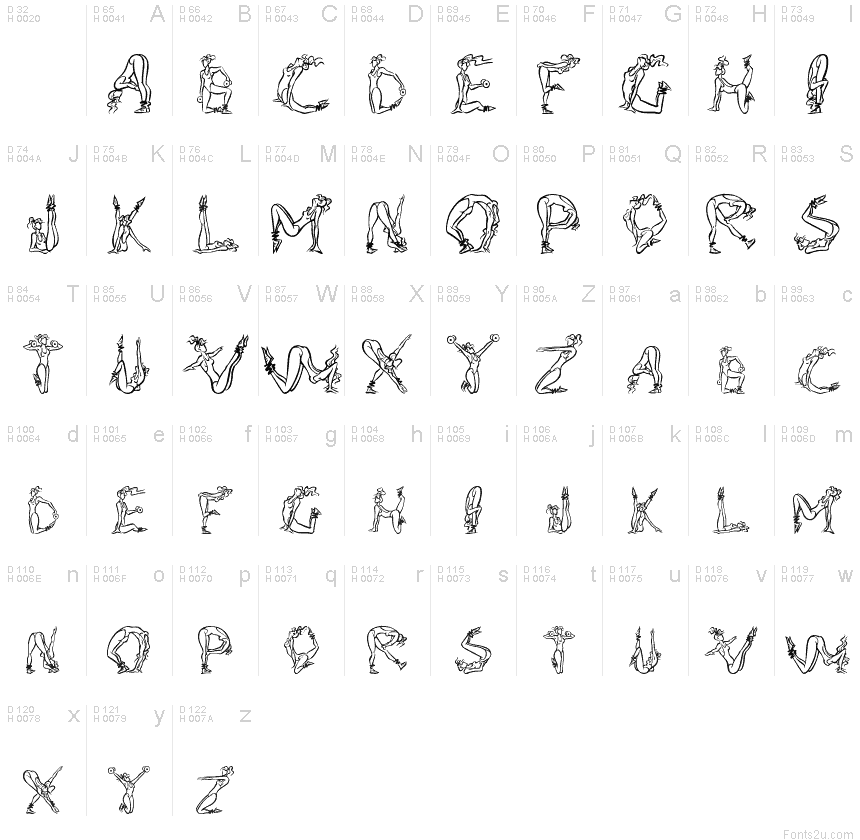
Alpha Fitness di Beeline Fonted by Miss Claude è un font display gratuito in stile cartoon che trasforma ogni lettera in una piccola scena di allenamento. Ogni carattere è disegnato con figure agili che si allungano, fanno equilibrio e posano, dando l'impressione che le parole siano letteralmente in movimento. I tratti disegnati a mano, dai contorni leggermente incerti, le conferiscono l'energia di un quaderno di schizzi — come scarabocchi ai margini di un diario di fitness — rendendo i titoli giocosi, dinamici e pieni di personalità.
Con Alpha Fitness, puoi dare un tocco di divertimento a poster di palestre, volantini per eventi benessere, programmi sportivi per bambini, grafiche per sfide di fitness, branding di studi di yoga o titoli editoriali stravaganti. Questo font gratuito dà il meglio di sé in grandi dimensioni, dove ogni piccolo personaggio è chiaramente visibile; abbinalo a un font sans serif pulito per il testo principale, in modo che i disegni rimangano i protagonisti.